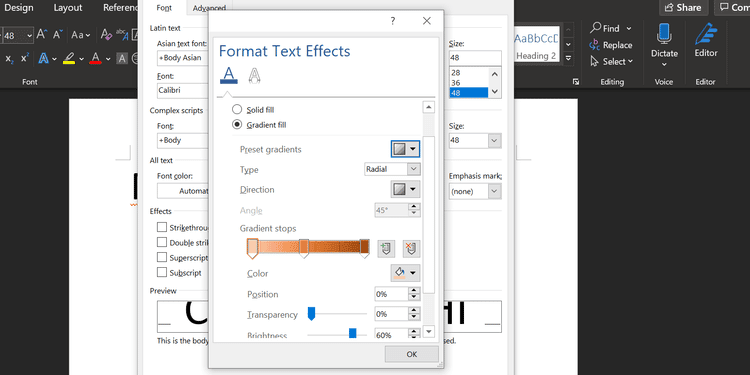
Solo vedere pagine di testo normale può far cadere le palpebre. I documenti Word non formattati indicano che questa lettura sarà frustrante e noiosa. Nessuno vuole sopportare quel tipo di noia.
Include Microsoft Word Ha molti strumenti che possono rendere il tuo testo più bello con caratteri estetici ed effetti sottili. Esagerare può riempire il documento di distrazioni, ma l'approccio ragionevole al design e all'arredamento aggiunge un importante interesse visivo per mantenere l'attenzione del lettore.
Ecco alcuni stili ed effetti dei caratteri per far risaltare il testo in Microsoft Word.
1. Installa i caratteri estetici per Microsoft Word
Uno dei modi più semplici per dare vita al testo in Word è aggiungere alcuni nuovi caratteri. Puoi trovare molti font gratuiti online, ma vale la pena dedicare un momento a considerare se desideri utilizzare il formato OTF o TTF prima di iniziare la ricerca.
Queste sono versioni leggermente modificate del carattere con dimensioni modificate: possono essere molto utili se stai cercando la perfezione, ma la maggior parte degli utenti sarà ben servita dalla sola versione normale.
Quindi seleziona semplicemente il nuovo carattere estetico dalle opzioni di formattazione in Microsoft Word.
2. Aggiungi un'ombra semplice
L'ombra esterna è una classica tecnica di progettazione grafica che puoi utilizzare per far risaltare il tuo testo. Word offre diversi modi per ottenere questo risultato e puoi utilizzare il menu Effetti testo e testo per farlo.
Innanzitutto, digita il testo che desideri e formatta le dimensioni e il carattere secondo le tue specifiche preferite: dovrai decidere come vuoi che appaia prima di creare la tua ombra. Seleziona il testo con il mouse, fai clic sull'icona Effetti di testo e caratteri (pulsante A blu), quindi seleziona Ombra seguito da opzioni di ombra.
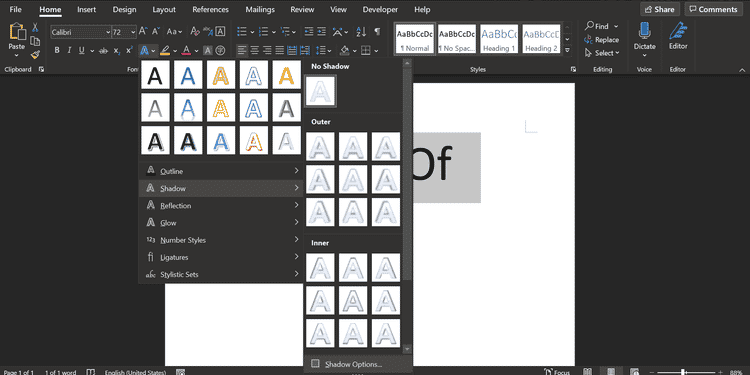
Si aprirà un nuovo menu sulla destra che consentirà di personalizzare la tonalità. O fai clic su un'opzione Preimpostazioni E scegli una delle tante opzioni di tonalità o regola tu stesso le varie impostazioni per creare una tonalità personalizzata.
Vedrai l'anteprima dal vivo a sinistra del menu ombra.
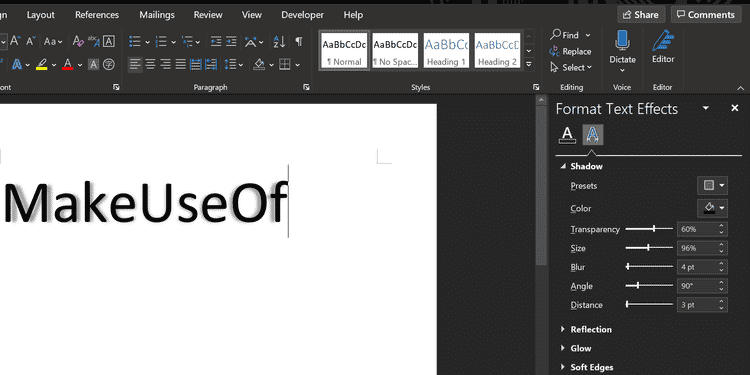
Continua a modificare le opzioni finché l'ombra non appare nel modo desiderato. È quindi possibile fare clic sull'icona X nell'angolo in alto a destra del menu ombra per chiuderlo. Word salva automaticamente le modifiche apportate al testo.
3. Aggiungi capolettera
Il capolettera è la prima lettera maiuscola di un paragrafo, che si trova spesso nei romanzi antichi. Microsoft Word può allestire il tuo documento con questo elemento decorativo che cattura l'attenzione in pochi secondi, offrendoti i mezzi per aggiungere interesse a un grande blocco di testo o semplicemente richiamare alla mente un'era classica.
Vai alla sezione Testo della scheda Inserimento E cerca il menu a tendina Proiezione. Sarai in grado di creare un capolettera molto semplice selezionando uno dei due fu gettato أو a margine Qui, ma per ottenere i migliori risultati, dovrai fare clic Opzioni di rilascio del personaggio consumabile , mentre è selezionata la prima lettera del paragrafo.
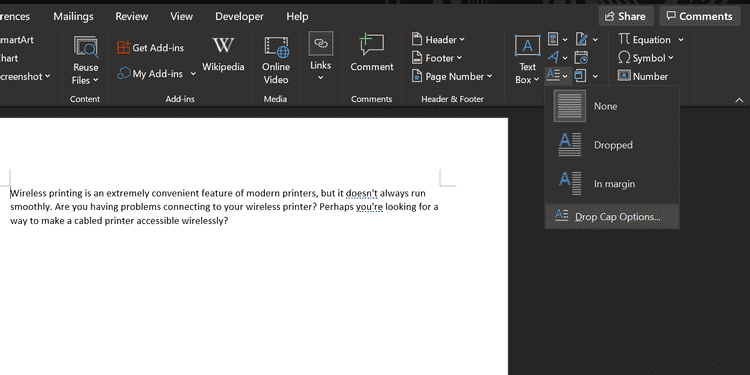
Individuare fu gettato Imposta la distanza dal testo su 0.2 cm (0.08 pollici). Potrebbe essere necessario regolare la quantità, a seconda del carattere che stai utilizzando e della scala con cui stai lavorando, ma il capolettera a volte può sembrare imbarazzante rispetto all'interlinea standard quando lasciato a 0.
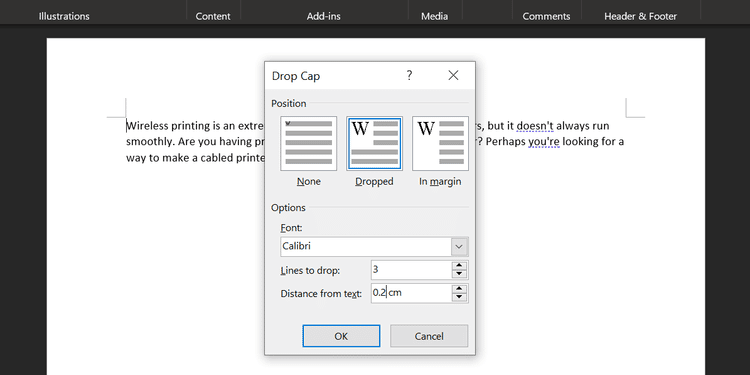
La scelta del carattere sarà la chiave per l'effetto complessivo. Un font sans può funzionare bene se il tuo obiettivo principale è un aspetto accattivante, ma una copertina più tradizionale può essere ottenuta con un font serif più semplice.
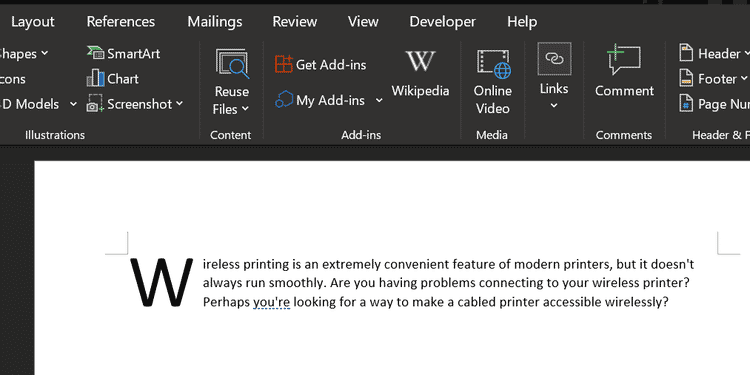
4. Usa effetti di testo
Se usati con noncuranza, gli effetti di testo disponibili in Microsoft Word possono facilmente ricordare i peggiori eccessi di WordArt. Tuttavia, fintanto che non ne fai un uso eccessivo, questi effetti possono dare al tuo documento un vero impatto visivo.
Per accedere al menu degli effetti di testo, vai alla scheda Home e fai clic sul pulsante a comparsa nella sezione Font.
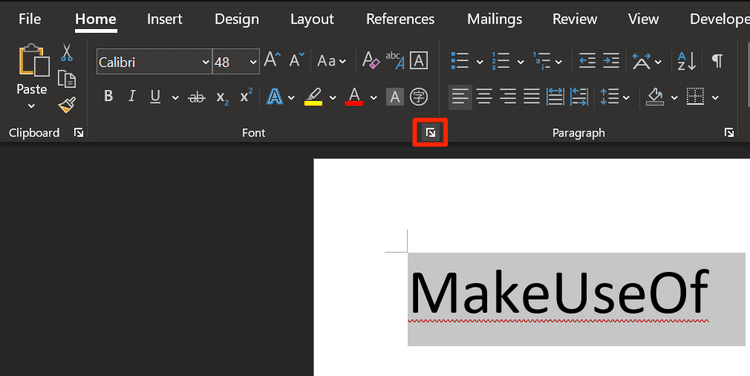
Quindi fare clic sul pulsante Effetti di testo nella finestra che si apre.
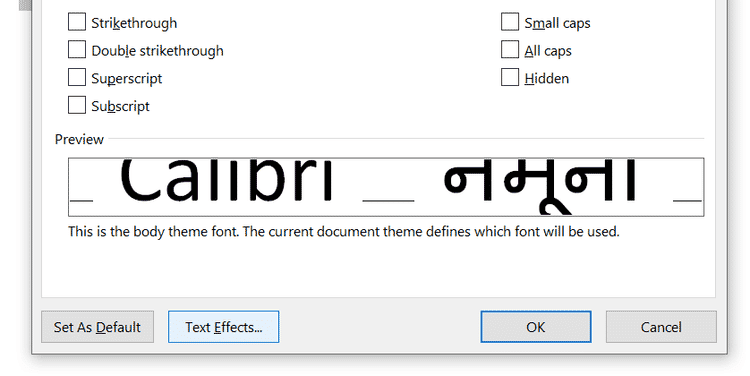
riempire il testo
L'opzione di riempimento del testo è un ottimo modo per aggiungere un po' di colore a un pezzo di testo. Un riempimento puro applicherà solo un colore alla tua selezione, cosa che può essere eseguita con meno complicazioni, ma l'opzione di riempimento sfumato offre molte sfumature per qualsiasi grafico in erba.
Fai scorrere il testo in Word
Con una buona formattazione, non solo il tuo testo ha un aspetto più gradevole, ma fornisce anche punti di ancoraggio per gli occhi e aiuta il lettore a scorrere il documento.
Ci sono molte regole di progettazione per Microsoft Word Che puoi seguire per dare un tocco professionale ai tuoi documenti. Vale la pena imparare queste regole se trascorri molto tempo con Word.